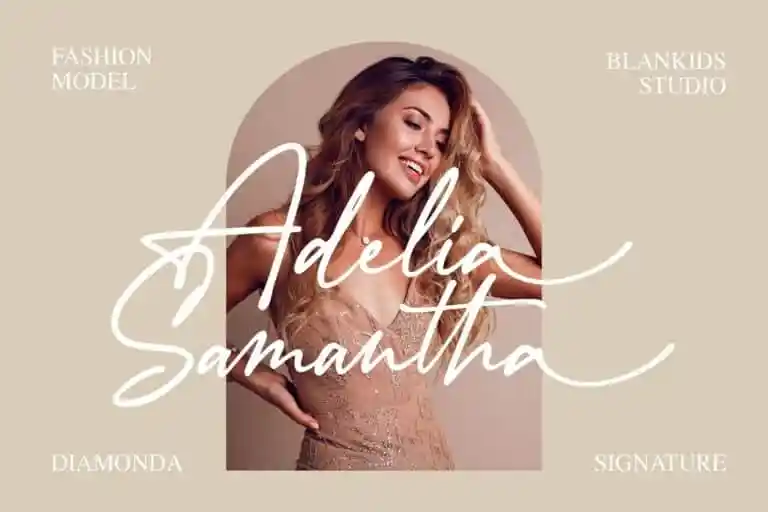
Diamonda Script Font – Download Grátis
Diamonda Script Font é uma elegante tipografia feminina que traz à tona swashes incríveis, adicionando um toque delicado às suas criações. Inspirada no estilo autêntico de uma assinatura, esta fonte é perfeita para design de exposição, criação de camisetas, decoração de casas e até mesmo para logotipos e sinalização da frase. A sua sofisticação suave faz dela a escolha ideal para qualquer projeto que deseje um ar feminino e delicado.